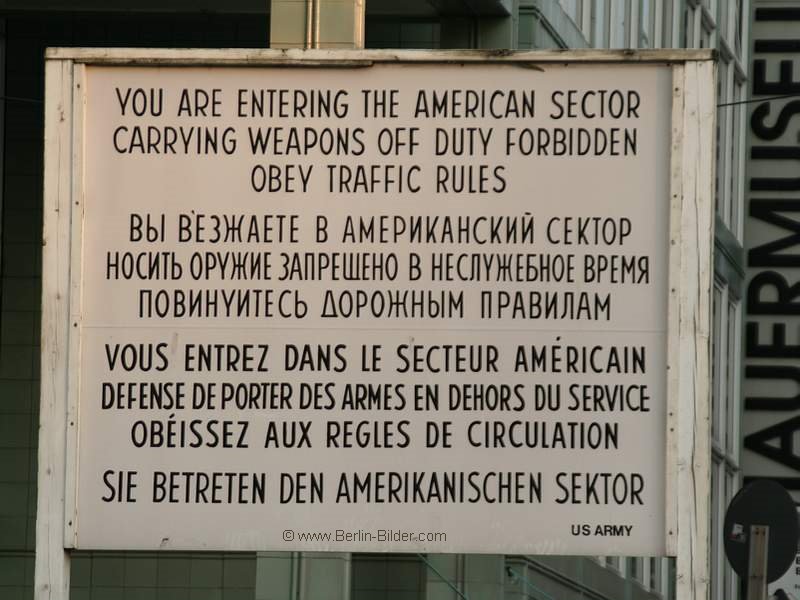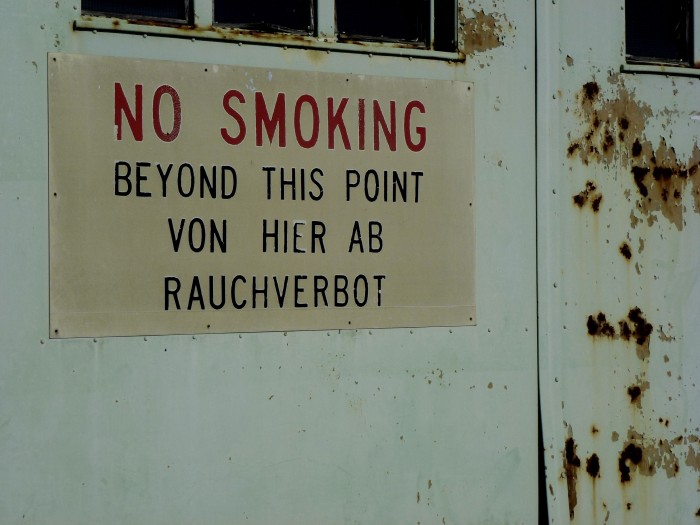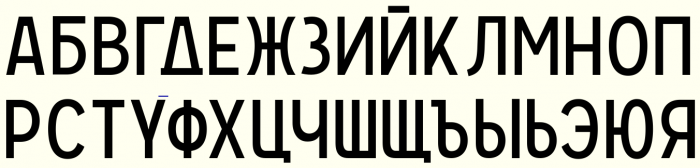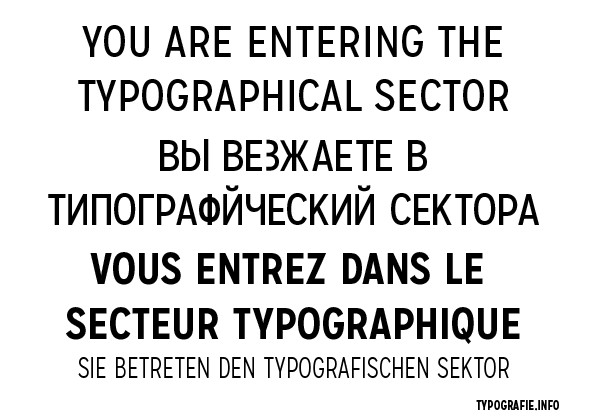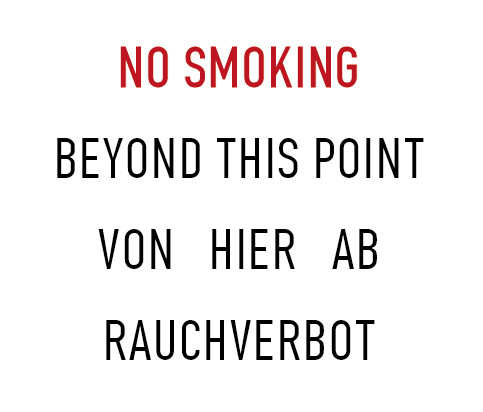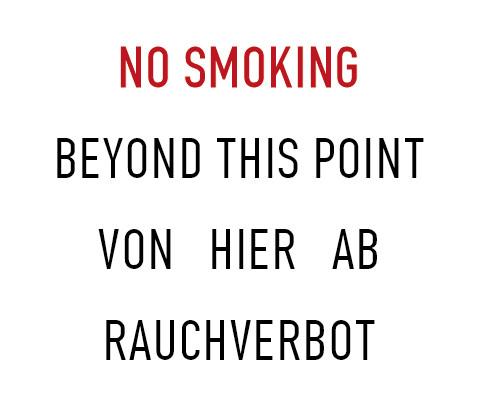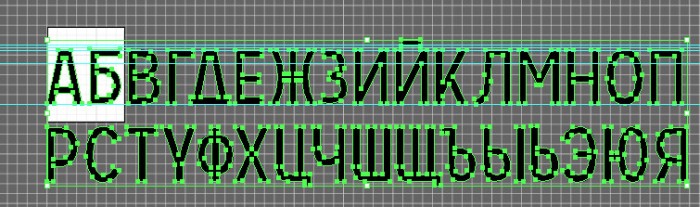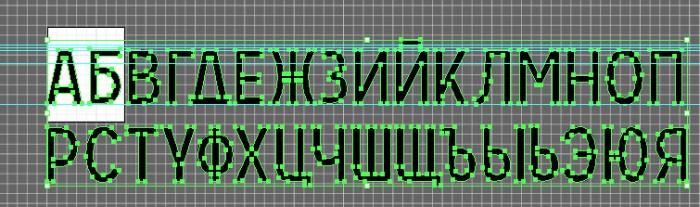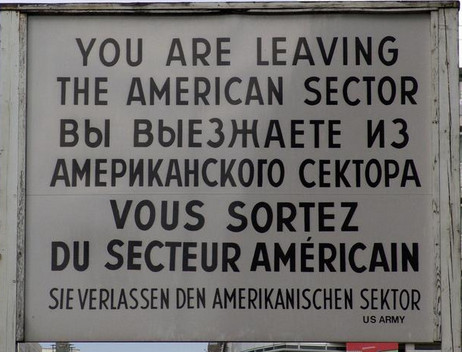
Mein erster Versuch Schild Checkpont Charlie Berlin
Habe mal was gebaut und ich hoffe es kommt der Originalschrift am nächsten.
Ist mein erster Gehversuch
und hier das Original
das "bI" wirkt recht schmal ist aber so breit wie ein "H"
Da muss man wohl doch ein PI auf den Kopf stellen.
oh oh... Ich will ja nix sagen, aber die Berliner Besatzungs-Beschilderung hatte schon eine interessante Typografie...
Wohl wahr Peter, wenn sie fettifg ist, kann ich sie dir ja mal schicken, zwecks Überprüfung. Bei den russischen Buchstaben sehe ich schon, dass da bei einigen Buchstabenkombinationen noch was gemacht werden muss. Wenn du dir die Rückseite anschaust werden dir vermutlich die Tränen kommen.
besonders das russische У / Y oder das Д was eher wie ein Delta ausschaut.
Stimmt, die Schriftr hat gewissermaßen einen amerikanischen Akzent.
In einer Doku über das Berlin der unmittelbaren Nachkriegszeit habe ich letztens Hinweisschilder, die von der sovjetischen Kommandatur erstellt wurden gesehen. Dieses Schild war zwar in lubenreinem Hochdeutsch abgefasst, aber die Glyphen hatten buchstäblich den "klang" eines Russen.
Hier war es besonders das K mit diesem geschwungenen Arm, aber auch einige Ziffern. Leider habe ich bislang keine Fotos dieser Schilder.
aus einem kyrillischen Font einen lateinischen zu machen ist et was einfacher
hier mal mit kyrillischen Buchstaben
РЕТЕЯ  dann noch das  "ja" spiegeln.. gleiches für N И usw. D gibt es leider nicht, könnte man aber aus einem Э . aber egal. muss man halt alles bauen. ich werde wahrscheinlich den Font noch so bestücken, dass man ihn halbwegs auf einer deutschen Tastatur schreiben kann. da ja keine Kleinbuchstaben benutzt werden, könnte man die kyrillischen Buchstaben dort hinlegen. mal schauen wie weit ich komme. Mit Typografie mit dem Font zu beginnen, wird sicher einige wundern, aber ursprünglich brauche ich den Font für ein historisches Projekt.
mir fällt beispielsweise die zu geringe Laufweite des englischen Textes auf, wobei die Original-Abstände sehr unregelmäßig sind. Der deutsche Text passt am besten für mein Laien-Auge.
Jau da muss noch einiges gemacht werden.
wie ich schon schrieb. ist mein erster Versuch überhaupt eine Schrift zu bauen. Da haben einige schon sehr viel mehr Erfahrung..
Catfont sei da nur als Beispiel genannt.
Ein schöner erster Aufschlag! Bei der Schrift muss ich an eine Kreuzung aus Interstate und Carrosserie denken.
ja die Schriften haben leider keine kyrillischen Zeichen..somit..muss man selbst was bauen. Dennoch danke für den Hinweis..denn die Carosserie hat in der Tat sehr viel Ähnlichkeit.
Vielleicht könntest du ja meine TGL 0-1451 verwenden?  Auch wenn die nicht so diesen Ami-Akzent hat.
nun gerade deshalb weil sie einen amerikanischen Akzent hat, wirkt sie authentisch. die TGL wäre wahrscheinlich für die "Ostseite" wirkungsvoller. ich schau mir mal die TGL an.
Nun, ich habe mir deine Schrift mal etwas genauer betrachtet.
Besonders kritisch, wenn du dann durch Spiegeln dann z.B. die kyrillischen Komponierst, bekommst du seltsame Kurvenverläufe ind sehr ungleiche Strichstärken. Besonders unglücklich geraten ist das З, das eigentlich mehr einer 3, als deb vom B abgeschnittenen Bäuchen gleicht, da musst du nuch ran.
Dann hast du ja ürsprünglich das Ziel gehabe, die Schrift des Schildesw vom Checkpoint Charly digital nachzubauen. Und dann baust du die kyrillischen Schriftzeichen nicht so nach, wie sie sind, sondern eher wie sie in der Standardform sein sollten. aber dann ist es eben nicht mehr die Schrift vom Schild.
Du hast ja beispielsweise das seltsame De und kyrillische U kritisiert. Im sinne des Standards isat das falsch, aber man KANN diese Buchstaben eben auch so schreiben, und es wird auch oft so gemacht, auch bei den Russen, das gilt auch für den einfachen graden Strich statt des Breve über dem langen I, gewrade wenn es um den Platz geht.
Ich habe mir mal deine kyrillischen zur Brust genommen, und etwas dran herumgezupft, um sie mehr wie auf dem Schild aussehen zu lassen (beim Normal-Schnitt):
Mein genereller Rat ist aber: Beginne am besten noch einmal bei Null, ohne einen Font als Rohmaterial heranzuziehen, Mach dir eine Vergrößerung vom Checkpoint-Schild, analysiere die Schrift darauf, aus welchen wiederkehrenden Bruchstücken die Buchstaben komponiert werden können, und zeichne nur genau diese, statt kompletter Buchstaben. Erst dann kannst du beginnen, aus diesen Elementen die Buchstaben zu kombinieren.
Zusatztip: Wenn ich eine Schrift mit gleichen Strichstärken zeichne, zeichne ich oft nur den Mittellinien-Vektor, die gleichmäßige Strichstärke ergibt dann die Funktion: Tools - Actions - Effects - Expand.
Ich treffe ab und zu ehemalige amerikanische Militärangehörige, die während des kalten Kriegs in Westdeutschland bzw. Berlin stationiert waren. Dass ich als Zwangswehrdienstverpflichteter ganz kurz vor dem Ende der Diktatur auf der anderen Seite stand, sorgt höchstes für einen Lacher, aber bereitet nie Probleme. Interessanterweise waren die GIs damals i.a.R. sehr viel mehr von unserer angeblichen Kriegslüsternheit überzeugt als wir von ihrer. Anscheinend funktionierte die amerikanische Propaganda besser als die sowjetisch-ostdeutsche.